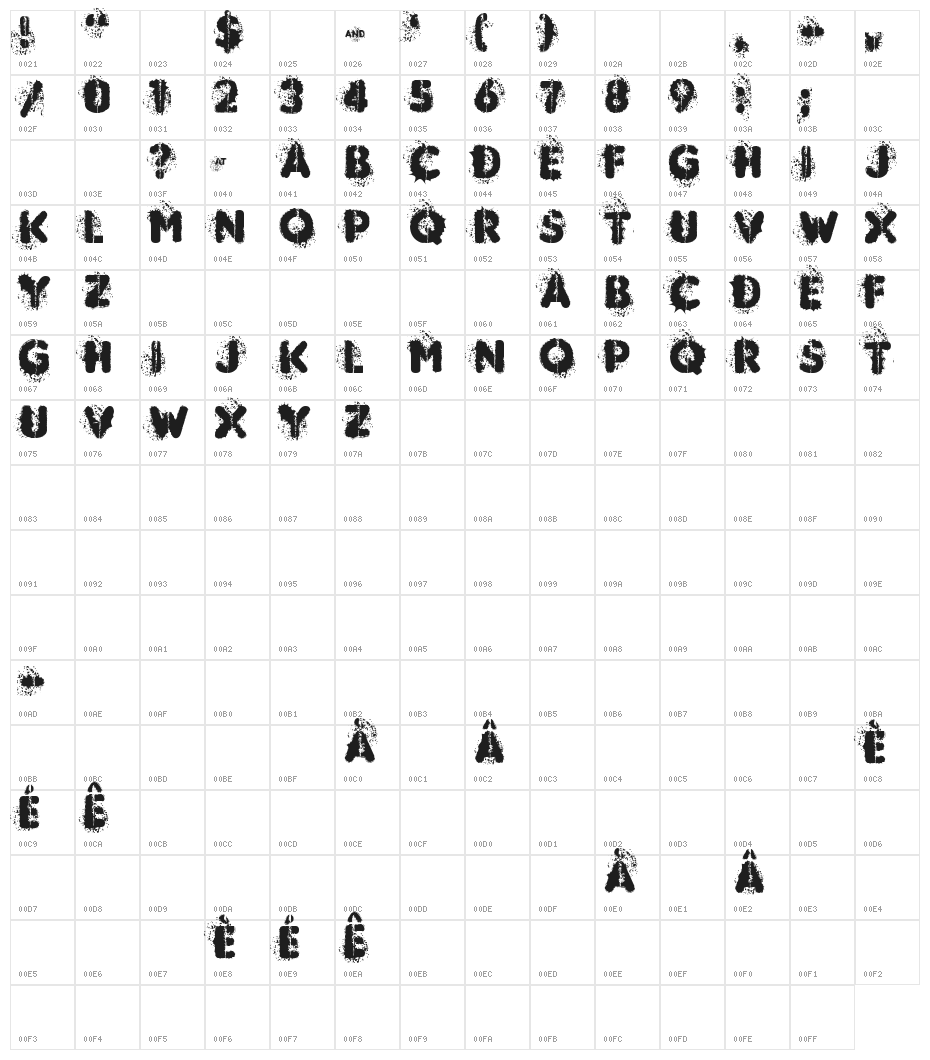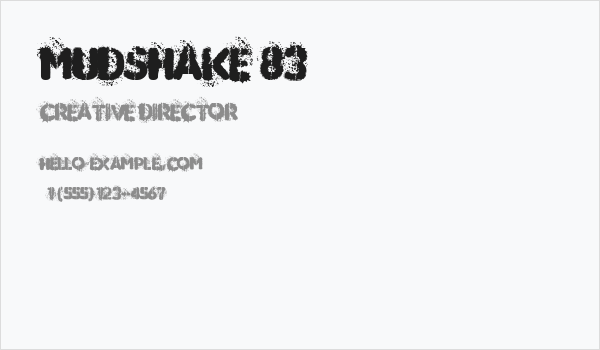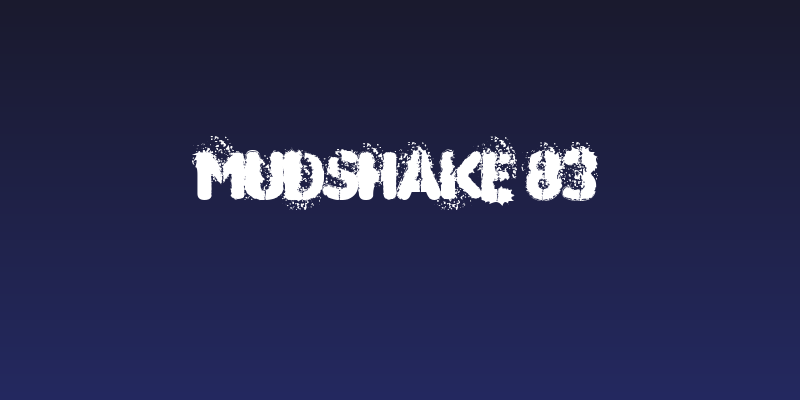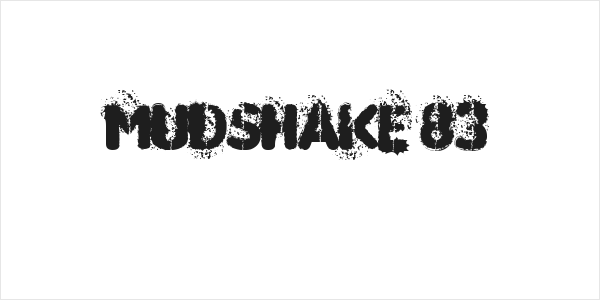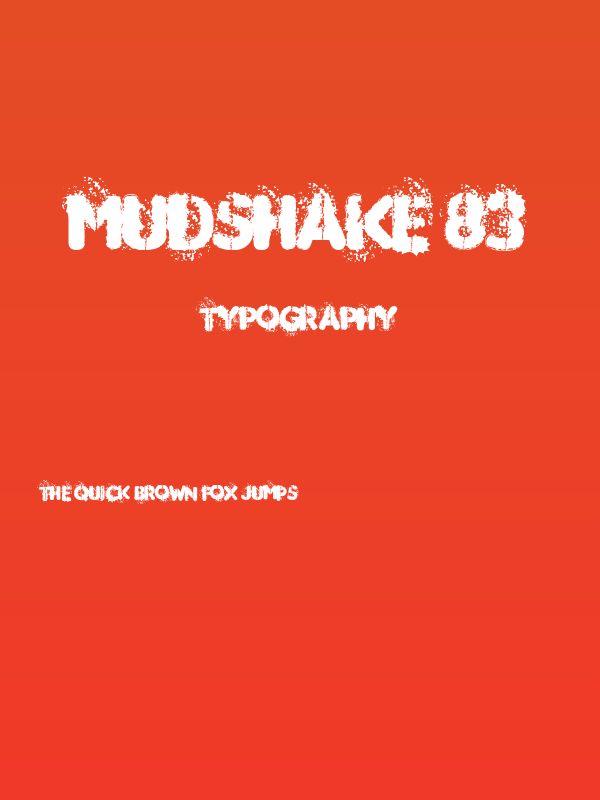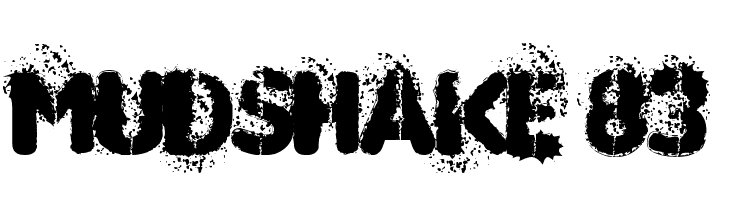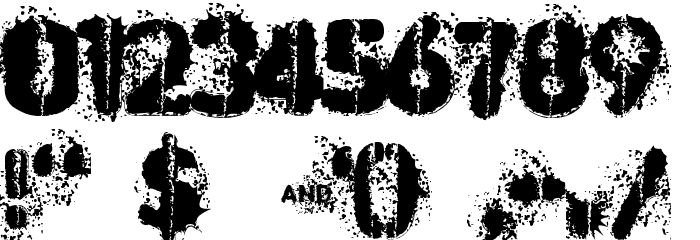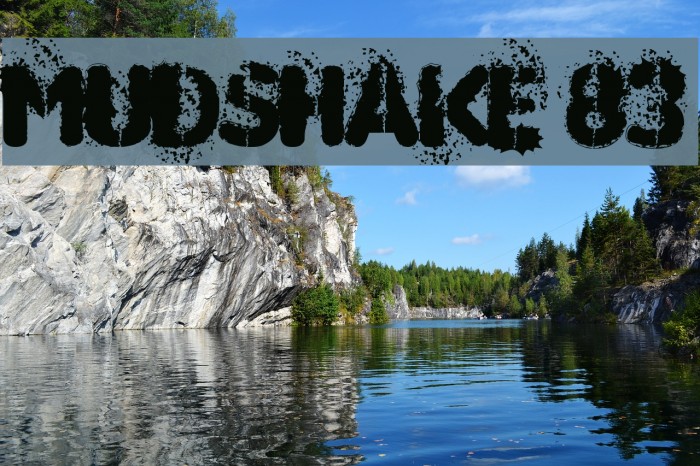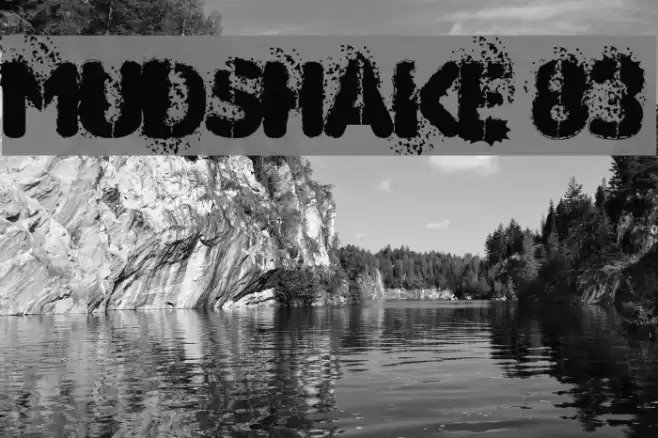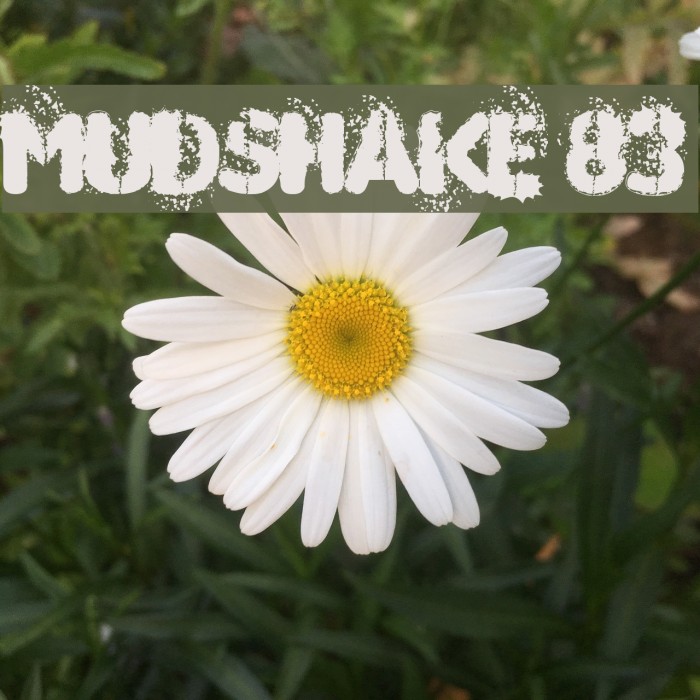
MUDSHAKE 83 Font
✎ Distorted Eroded
| Categorías | Distorted Eroded |
| Estilo general | Urban, Edgy, Distressed |
| Proyectos propuestos | Ideal for posters, album covers, streetwear branding, and event flyers that require a bold, edgy look. |